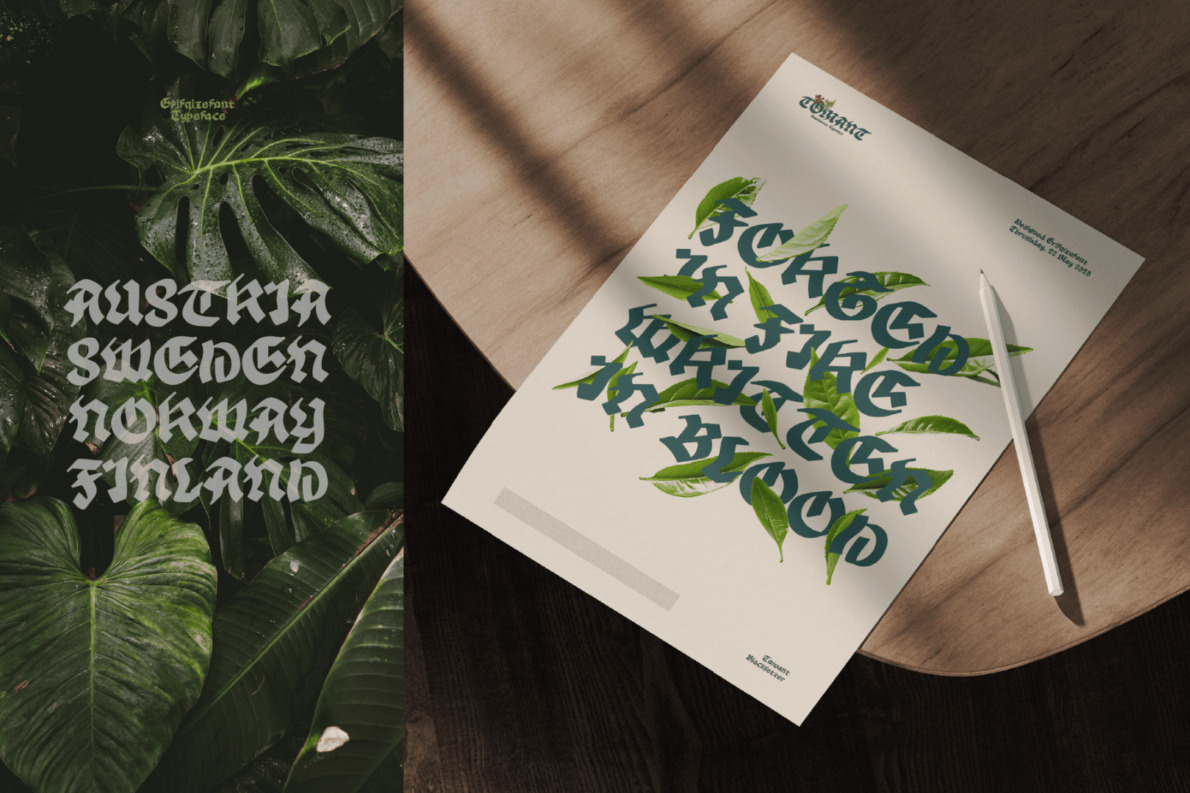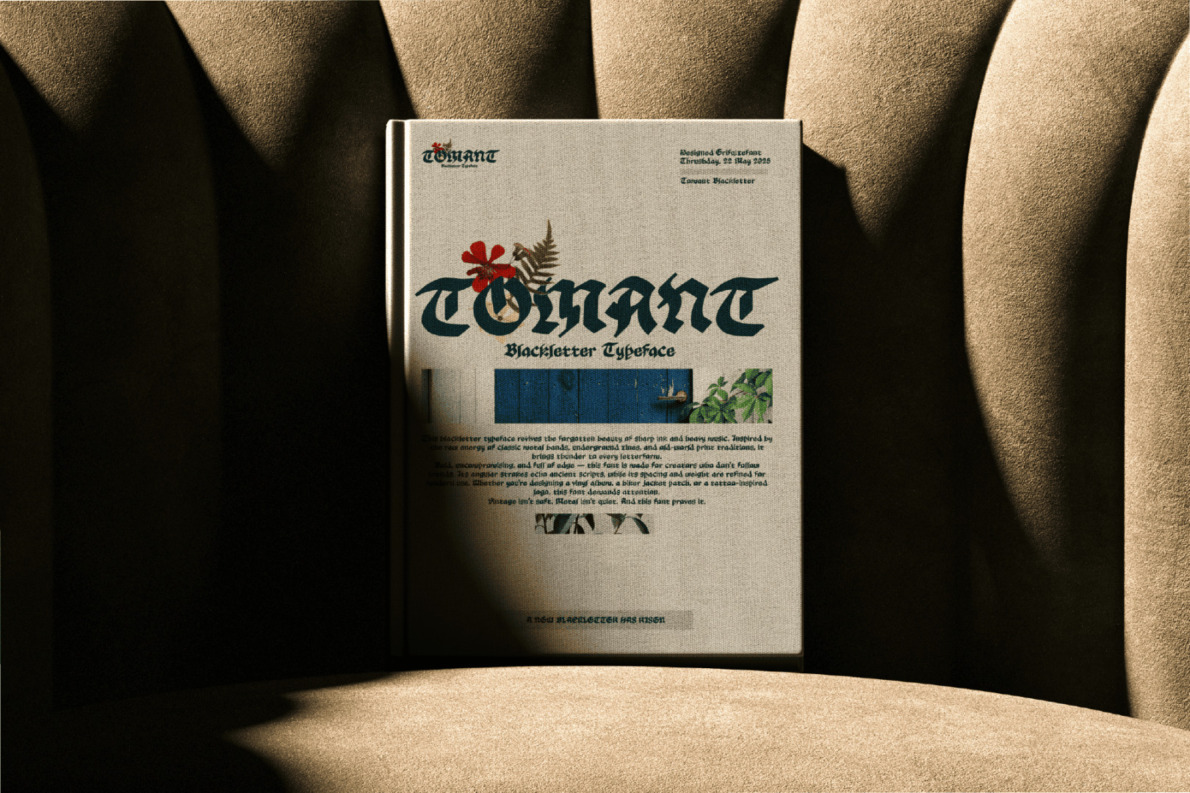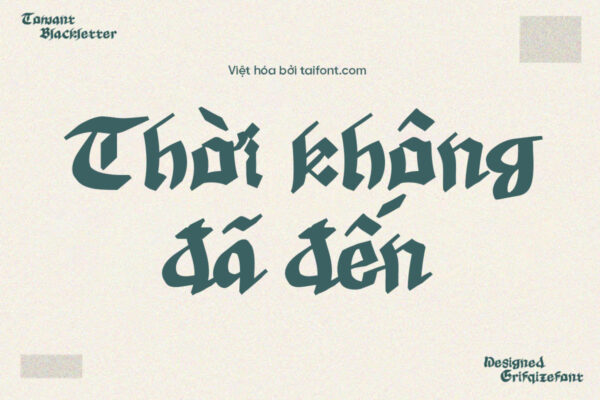
TF Tomant Blackletter Việt hóa là một font chữ trang trí đầy đặc sắc và ấn tượng, mang đậm phong cách Gothic cổ điển với những đường nét góc cạnh và mạnh mẽ. Khác biệt hoàn toàn so với các font thông thường, Tomant Blackletter toát lên vẻ uy nghi, bí ẩn và đầy quyền lực, tạo điểm nhấn độc đáo cho mọi thiết kế.
Font chữ này là lựa chọn lý tưởng cho các dự án muốn thể hiện sự độc đáo, táo bạo và có tính nghệ thuật cao, ví dụ:
- Thiết kế logo và nhãn hiệu: Dành cho các thương hiệu muốn tạo ấn tượng mạnh mẽ, mang đậm tính biểu tượng hoặc có phong cách vintage, rock, hoặc ma mị.
- Thiết kế áo thun, hình xăm: Thể hiện cá tính riêng, tạo điểm nhấn ấn tượng cho trang phục hoặc hình vẽ trên cơ thể.
- Poster và bìa sách: Đặc biệt phù hợp cho các tác phẩm có chủ đề lịch sử, giả tưởng, kinh dị hoặc mang tính chất nghệ thuật.
- Thiết kế liên quan đến âm nhạc: Tạo hiệu ứng mạnh mẽ cho bìa album, poster sự kiện âm nhạc.
Với TF Tomant Blackletter Việt hóa, bạn có thể dễ dàng tạo ra những thiết kế không chỉ đẹp mắt mà còn đầy cá tính và sức hút, giúp tác phẩm của bạn thực sự nổi bật giữa đám đông.